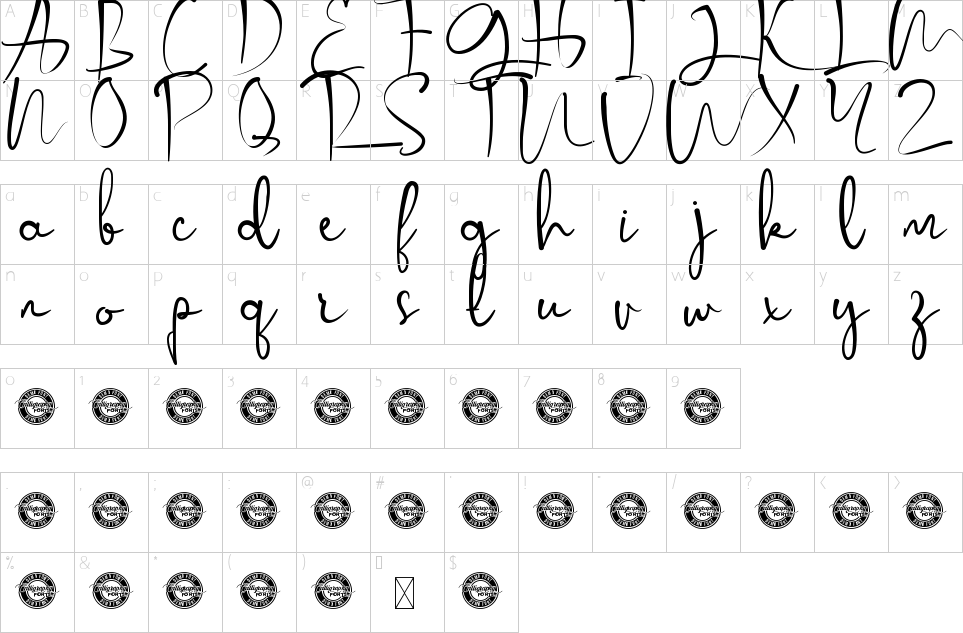
Aqui está uma descrição envolvente para a página de download da font ‘Golden Sheer Font’, adaptada aos requisitos fornecidos: Através deste catálogo de recursos gráficos, você encontra a elegante e sofisticada ‘Golden Sheer Font’. Inspirada no estilo artístico e na delicadeza do chamado, esta fonte é perfeita para trabalhos de design de qualidade. Desenvolvida por CalligraphyFonts, ela foi projetada para oferecer uma aparência sofisticada e envolvente, adequada a vários tipos de projetos. Seja você um designer gráfico profissional ou apenas iniciante no mundo do design, essa font é uma ótima opção. Com seu estilo chamativo e arredondado, ‘Golden Sheer Font’ pode tornar qualquer projeto único e memorável. Com mais de 1800 downloads, esteve sempre em alta popularidade entre os criativos que buscam um recurso para criar texturas sofisticadas ou trabalhos artísticos cheios de emoção. Se você está procurando por uma fonte gráfica que não só oferece beleza visual, mas também valoriza o design como arte, então ‘Golden Sheer Font’ é definitivamente o seu ponto final.